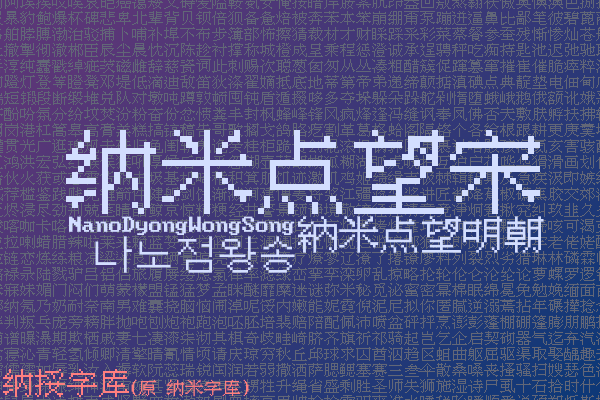
做纳米点望宋这副字体,底子其实就靠三大块料慢慢揉合在一起。最里头的主干骨架,直接拿ET3中文系统里抽出来的原始点阵来打底,先把整个字的像素比例和结构重心给定实,免得后续扩缩或者调整字重的时候整体变形。旁边需要过渡的地方,就去KC7中文系统里翻点阵数据补进去,专门对付那些笔画走向有点不一样、衔接处容易露馅的转折区。要是遇到底稿里根本没收录的字头,只能顺着老版本那种沉稳的气韵,一笔一划自己重新描一遍,非得让笔画的胖瘦和留白的呼吸感跟原版严丝合缝才行。等到这几拨素材都凑齐了,还只是打好了地基。真正费神的还在后面,得把外头提溜进来的像素格子和手工定型的字形挨个摆在一块儿对,拿辅助线去卡每一个切角的弧度、量每一段间距的空隙。来回校验好几轮,确认各个部件咬合顺畅、横平竖直都不走样,这才算真正把这套点阵字体严严实实地搭了起来,落笔定案。